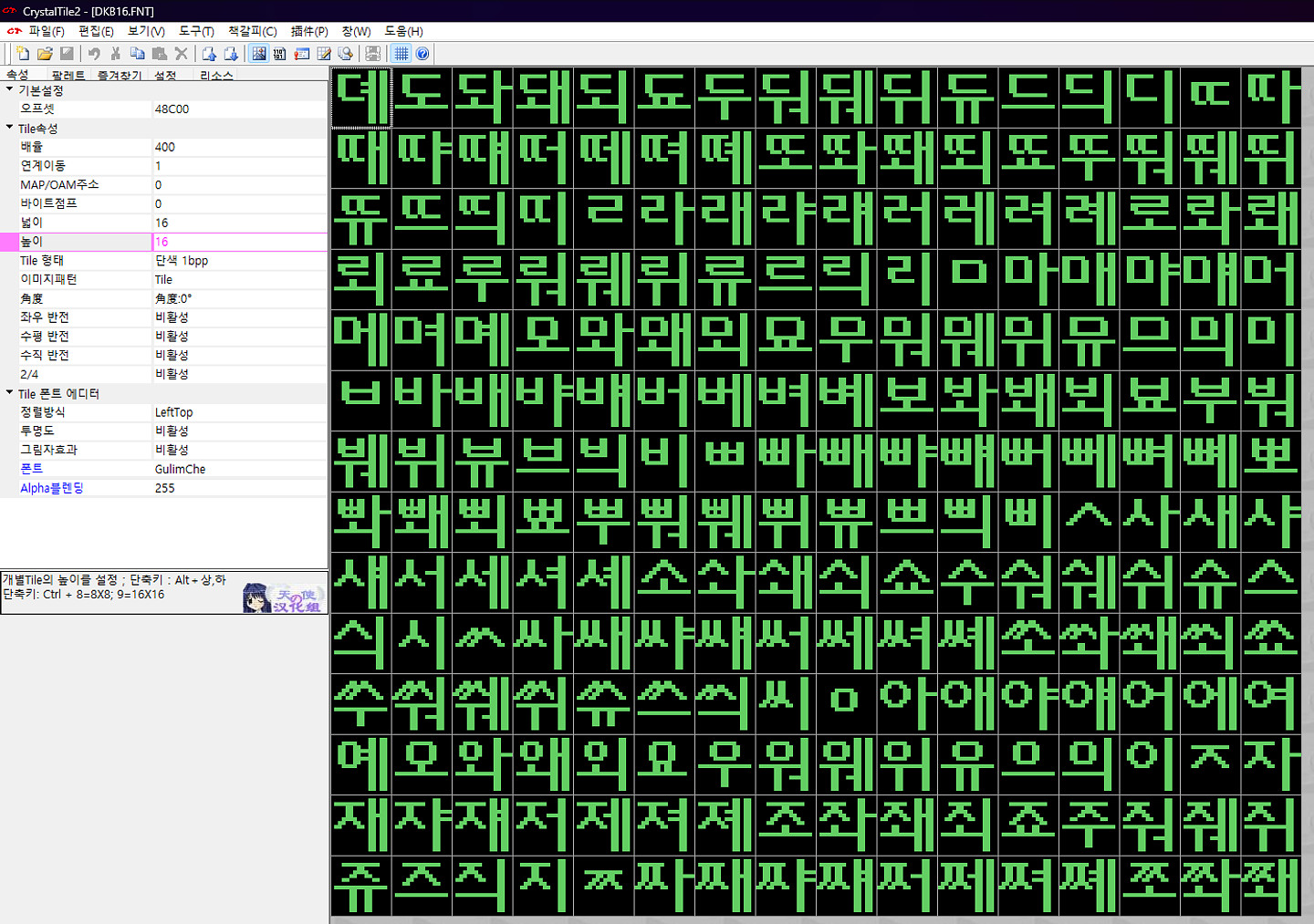
무슨 폰트인지 궁금합니다!!
DKB16
당시 도깨비한글에 사용된 폰트 같습니다. 비트맵 폰트이기에 현시점에선 직접 폰트를 아웃라인으로 변환하지 않는 한 사용이 불가합니다. https://megalock.co.kr/sub4.html 아웃라인으로 변환할 경우 'fnt 파일을 bdf로 변환 → 폰트포지 등으로 비트맵 형태를 따라 자동으로 아웃라인 그리기 → 아웃라인 형식으로 저장' 과정을 거쳐야 합니다만, DKB16.FNT가 일반적인 폰트 형식이 아니기에 과정이 더 어려울 듯 합니다. 첨부한 스크린샷의 GulimChe와는 연관이 없습니다.